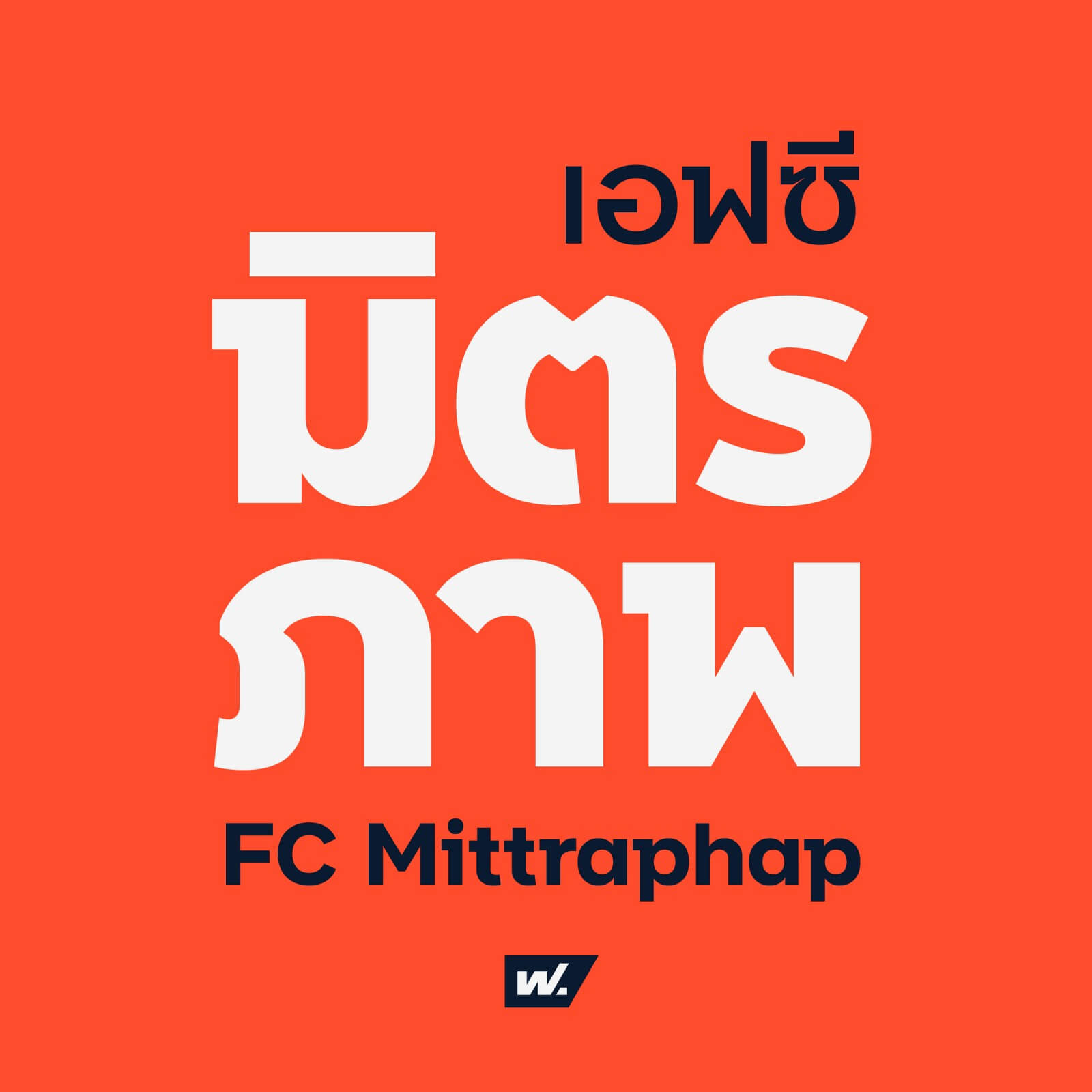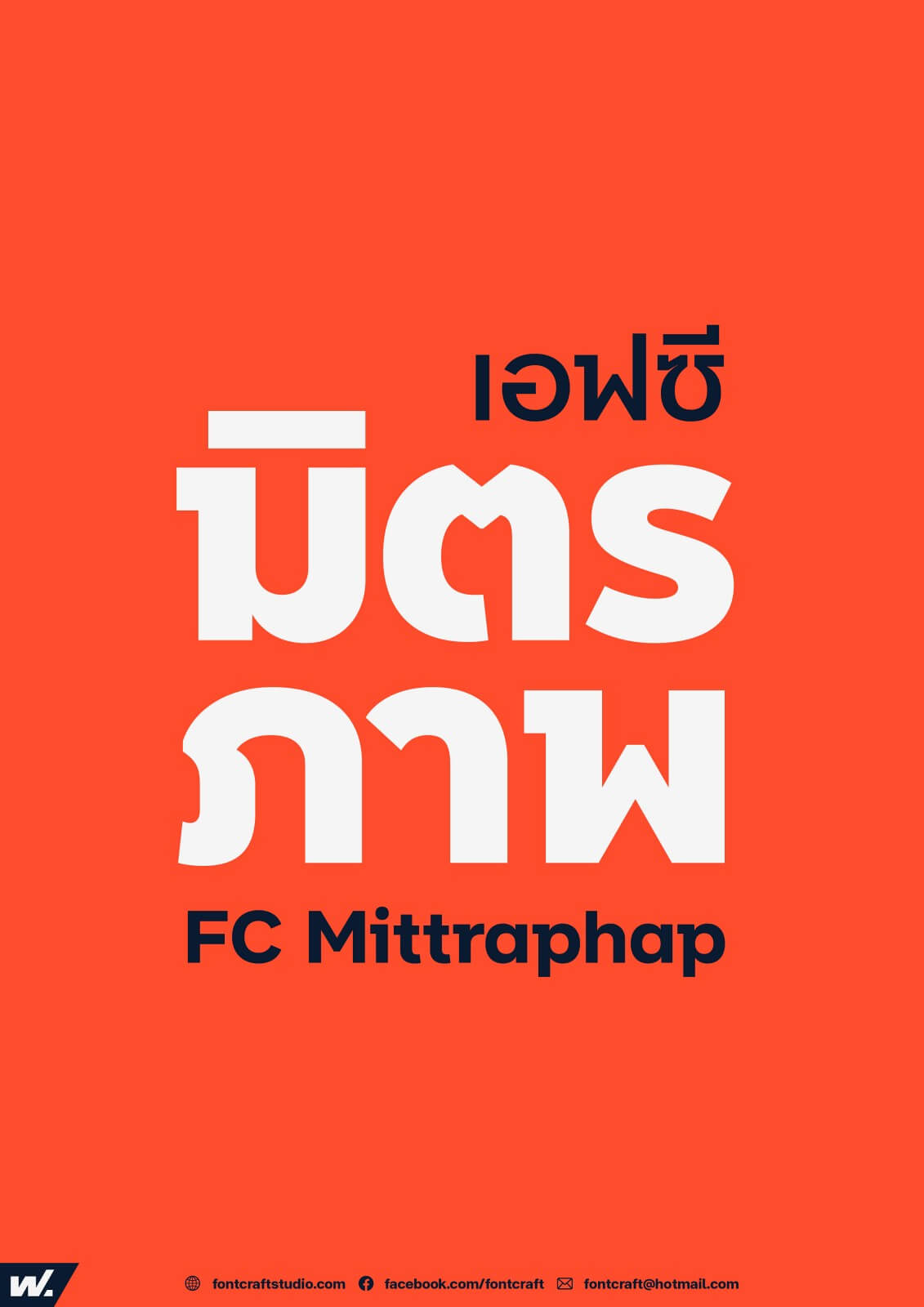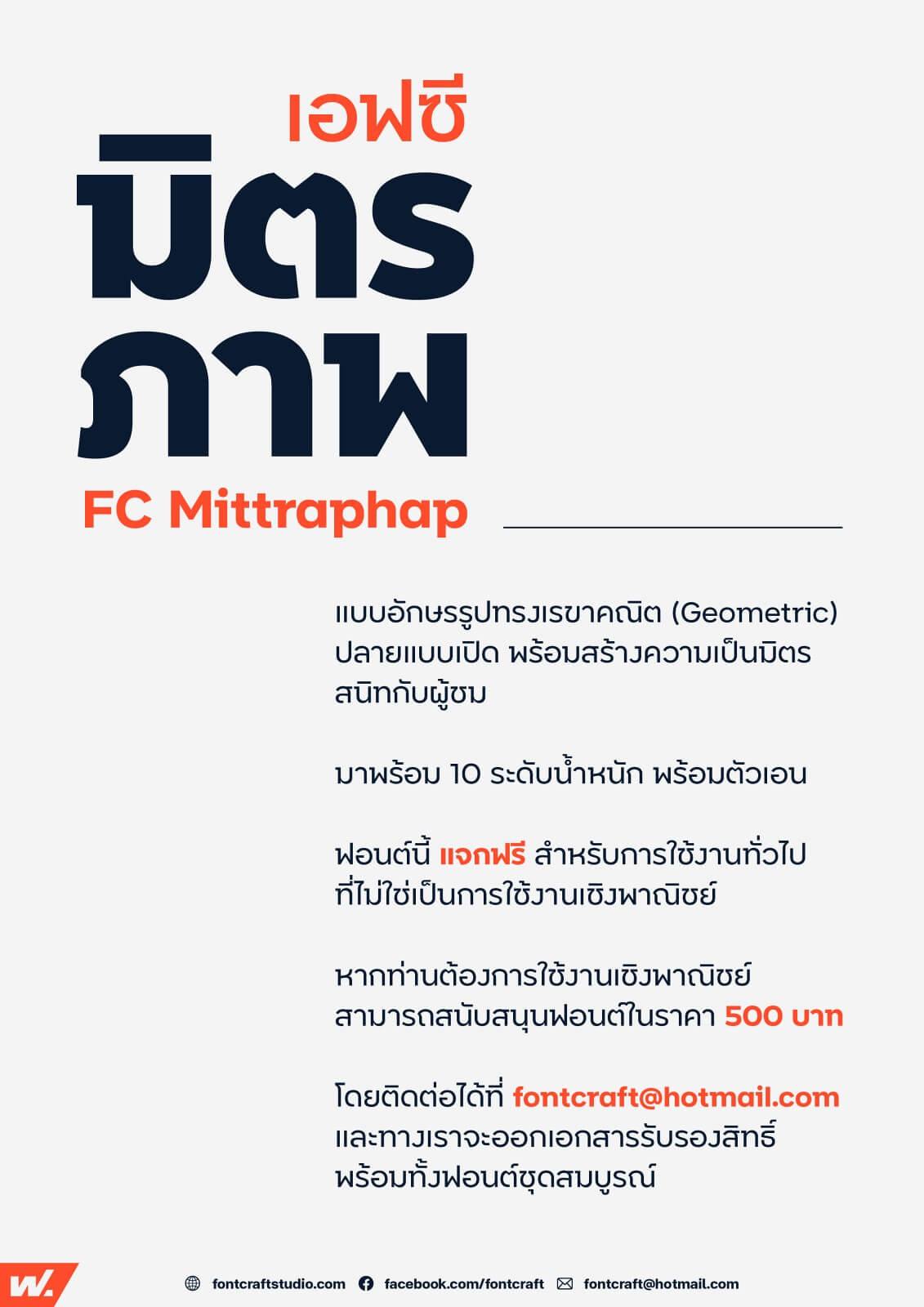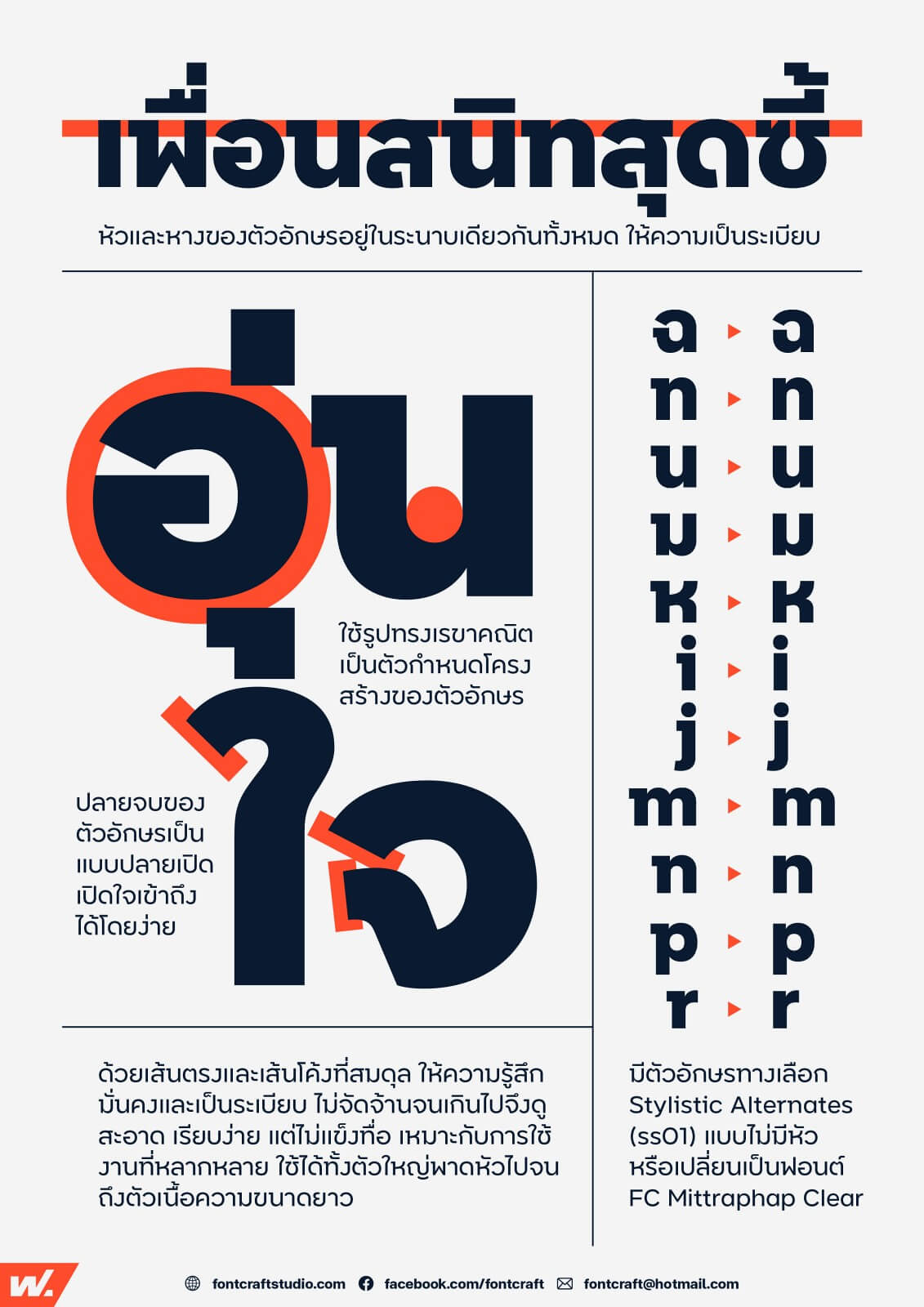
เอฟซี มิตรภาพ (FC Mittraphap)
แบบอักษรรูปทรงเรขาคณิต (Geometric) ปลายแบบเปิด พร้อมสร้างความเป็นมิตร สนิทกับผู้ชม
ด้วยเส้นตรงและเส้นโค้งที่สมดุล ให้ความรู้สึกมั่นคงและเป็นระเบียบ ไม่จัดจ้านจนเกินไปจึงดูสะอาด เรียบง่าย แต่ไม่แข็งทื่อ เหมาะกับการใช้งานที่หลากหลาย ใช้ได้ทั้งตัวใหญ่พาดหัวไปจนถึงตัวเนื้อความขนาดยาว
มีน้ำหนักให้เลือกใช้ 10 ระดับ พร้อมตัวเอนรวม 20 สไตล์ มี Variable Font แยกจากชุดปกติ และมีตัวอักษรทางเลือก Stylistic Alternates (ss01) แบบไม่มีหัวหรือเปลี่ยนเป็นฟอนต์ FC Mittraphap Clear